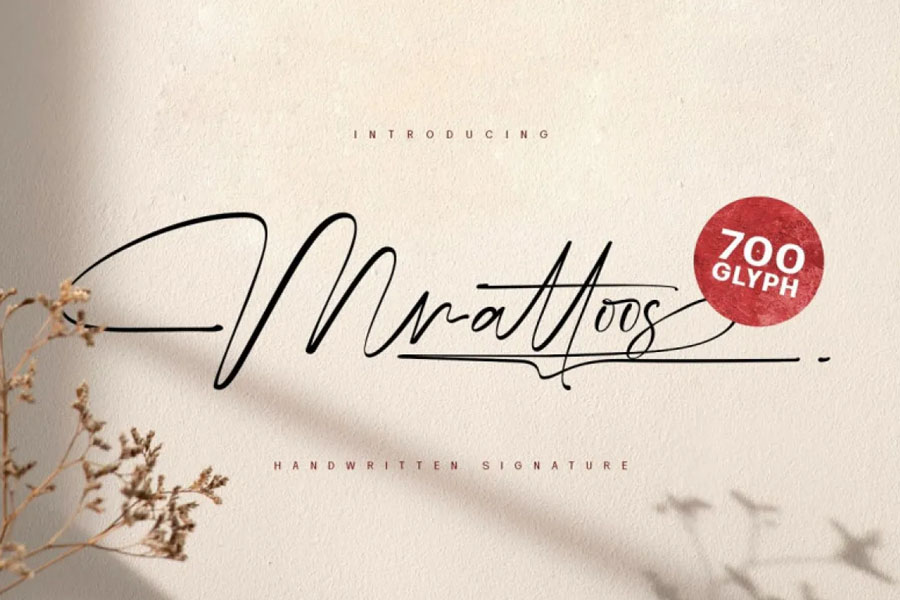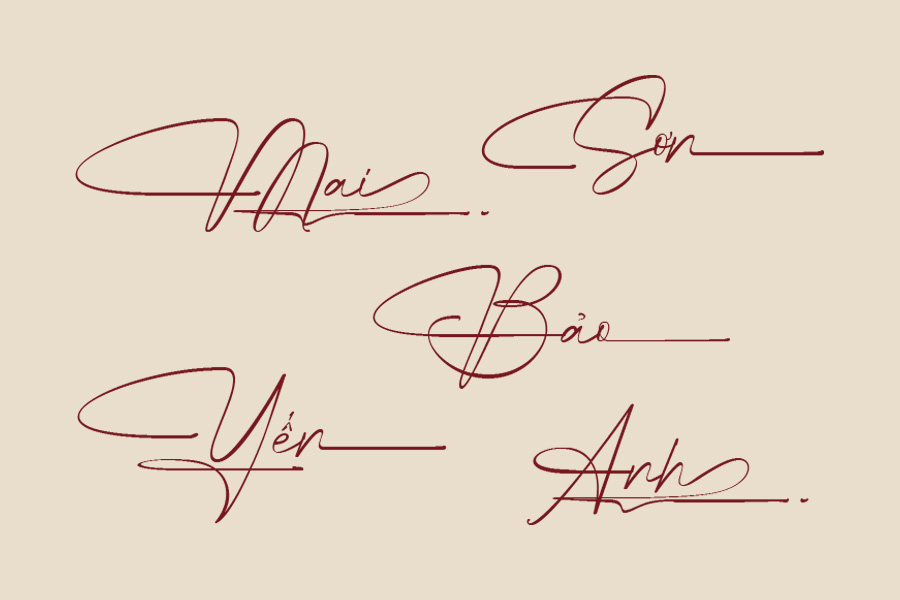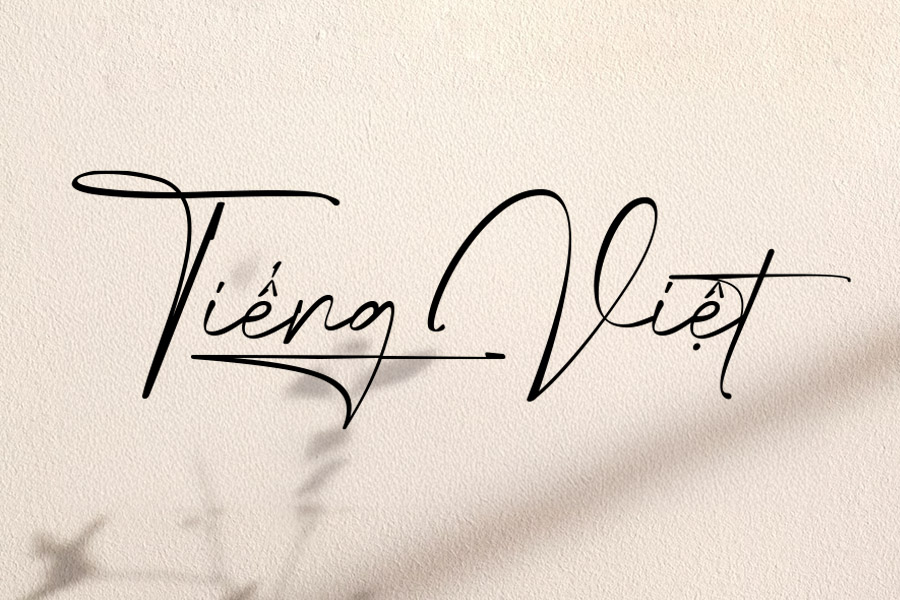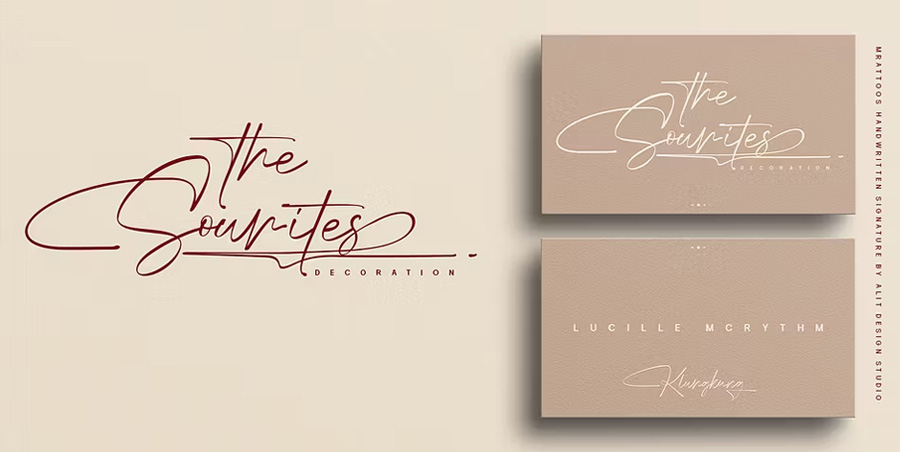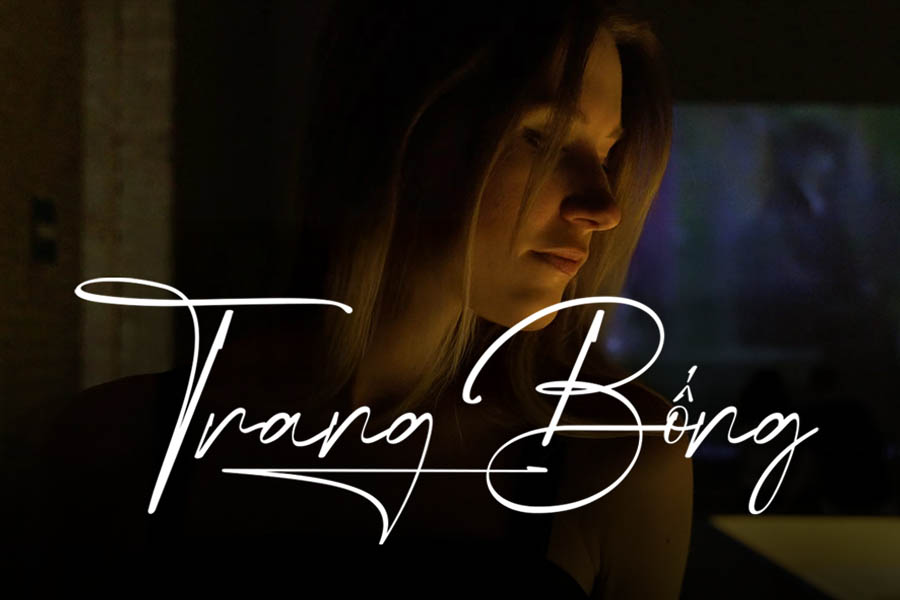
[Tải về] Font chữ ký viết tay đẹp TH Mrattoos Regular Việt hóa hoàn chỉnh
Tác giả Alit Suarnegara
Nếu bạn đang tìm kiếm một kiểu chữ mềm mại, tự nhiên như nét bút viết tay, nhưng vẫn đủ thanh lịch để sử dụng trong thiệp cưới, thư mời hay thiết kế thương hiệu, thì TH Mrattoos Regular chính là lựa chọn lý tưởng.
Với nét chữ mảnh, nghiêng nhẹ, đậm chất cá nhân nhưng không rối rắm, bộ font này mang đến cảm giác gần gũi, cảm xúc và đầy tính nghệ thuật – đặc biệt phù hợp với những thiết kế mang tính cá nhân hóa cao như chữ ký logo, branding cho thương hiệu nữ tính.
II. Giới thiệu chung về font Mrattoos
TH Mrattoos Regular là phiên bản Việt hóa của font chữ Mrattoos Regular – được sáng tạo bởi Alit Suarnegara, một nhà thiết kế đến từ Indonesia, thuộc studio nổi tiếng Alit Design. Font gốc mang phong cách viết tay cá tính, thường được dùng trong thiết kế bao bì, logo, và thiệp cưới ở thị trường quốc tế.
Phiên bản Việt hóa được thực hiện bởi team S99.VN, với tên gọi mới là TH Mrattoos, đảm bảo hỗ trợ đầy đủ tiếng Việt, giữ nguyên tinh thần thiết kế mềm mại, đồng thời tối ưu lại dấu thanh, cấu trúc ký tự để sử dụng linh hoạt trên các nền tảng thiết kế phổ biến.
III. Đặc điểm nổi bật của TH Mrattoos
Điểm đầu tiên khiến TH Mrattoos thu hút ánh nhìn chính là nét chữ thanh mảnh, hơi nghiêng về bên phải, như nét bút viết tay lướt trên giấy. Nhờ cấu trúc nét viết liền mạch, font tạo cảm giác chân thật và duyên dáng, phù hợp với nhiều ngữ cảnh sáng tạo.
Bên cạnh đó, Mrattoos không phải là một font viết tay đơn điệu. Bộ glyph thay thế phong phú giúp từng chữ cái có thể biến hóa linh hoạt – từ đơn giản, nhẹ nhàng đến phá cách, nghệ thuật. Đây là lựa chọn hoàn hảo cho các nhà thiết kế đang tìm kiếm font chữ thể hiện chất riêng trong thiết kế chữ ký, watermark, hoặc các ứng dụng cần dấu ấn cá nhân mạnh mẽ.
IV. Phông chữ có nhiều glyph thay thế đa dạng
Một trong những giá trị nổi bật nhất của TH Mrattoos nằm ở kho glyph thay thế (alternate glyphs) vô cùng phong phú. Điều này cho phép bạn tùy chỉnh từng ký tự để tạo ra những dòng chữ không lặp lại, độc bản và mang đậm dấu ấn cá nhân.
Ví dụ: bạn có thể sử dụng các biến thể đầu chữ mềm mại, chữ giữa đơn giản và chữ kết thúc có phần “vẩy chữ” cách điệu để tạo ra hiệu ứng như đang viết tay.
V. Hỗ trợ tiếng Việt và khả năng tương thích mạnh mẽ
TH Mrattoos đã được Việt hóa hoàn chỉnh, bao gồm đầy đủ các ký tự và dấu tiếng Việt như: ă, â, ê, ô, ơ, ư, đ, cũng như các dấu thanh: sắc, huyền, hỏi, ngã, nặng.
VII. Đánh giá tổng quan & gợi ý sử dụng
Nếu bạn thích những kiểu chữ mềm mại, có chút bay bổng và mang đậm dấu ấn cá nhân thì TH Mrattoos Regular chắc chắn sẽ khiến bạn ưng ý. Font này rất hợp để dùng trong các thiết kế cần sự tinh tế và cảm xúc, như:
• Thiệp cưới, thư mời trang trọng
• Logo cá nhân, thương hiệu handmade
• Watermark ảnh cưới hoặc ảnh nghệ thuật
Tuy nhiên, vì là font viết tay nên bạn không nên dùng cho văn bản dài hay size chữ quá nhỏ – dễ gây mỏi mắt khi đọc. Để thiết kế trông hài hòa hơn, bạn có thể kết hợp TH Mrattoos với một font không chân như Lato, Poppins hoặc TH Sophia để làm phần nội dung, giữ bố cục rõ ràng và đẹp mắt.